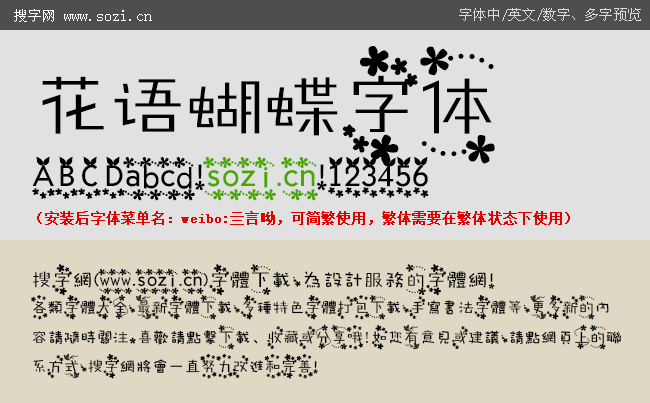
花語蝴蝶字體
搜字網(wǎng)給大家提供一款有趣的手機中文字體下載。名為花語蝴蝶字體,這款手機中文字體以黑體為原形,字體結(jié)構(gòu)進行了變化,筆畫雖然橫平堅直,但通過結(jié)構(gòu)的趣味變化,并且插入了一些卡通圖案,變成了一款十分卡通的POP字形,非常適合喜歡個性的朋友在手機上安裝使用。